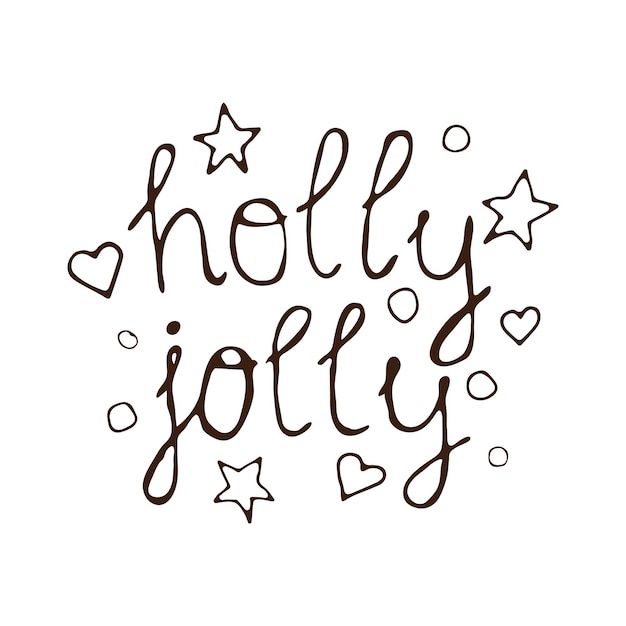
Prosta elegancka kaligrafia Boże Narodzenie napis Holly Jolly Kreatywny wektor typografia projekt z gwiazdami mrówka płatki śniegu Odosobniona czarno-biała ilustracja